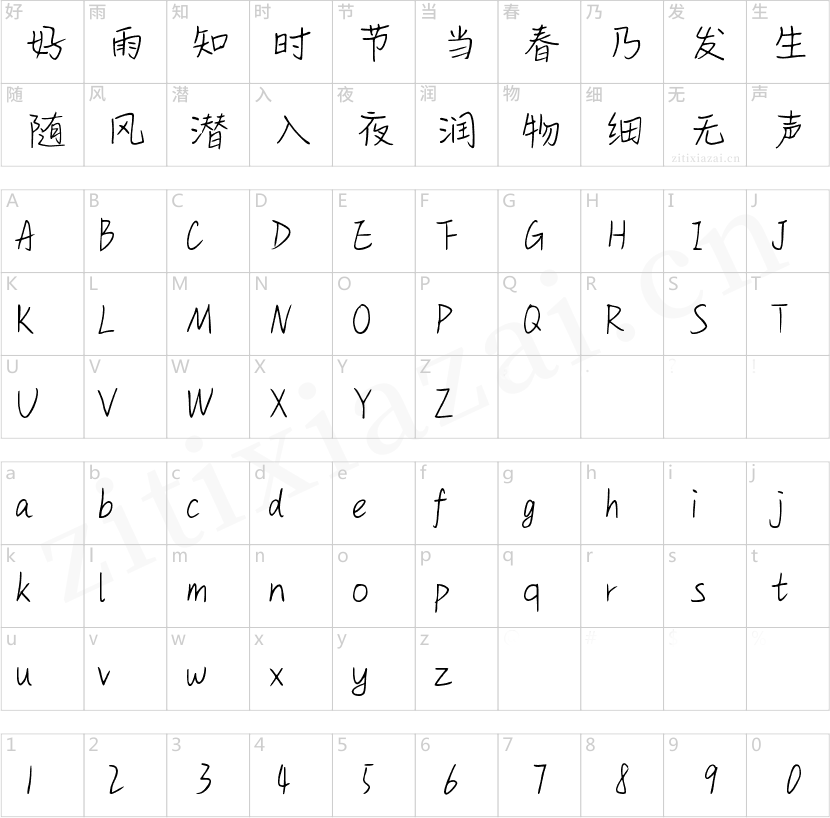
Aa嘟嘴卖萌
Aa嘟嘴卖萌字体
Aa嘟嘴卖萌是一款非常具有艺术性的字体,它的设计灵感来源于对古典艺术的研究,同时又融入了现代字体设计的元素。字形优美,笔画粗细变化自然,给人以大气、典雅的感觉。Aa嘟嘴卖萌是一款既传统又现代的字体,它的设计充满艺术感,美观大方,实用性也非常强。无论是对于设计师还是对于普通读者来说,都是一种非常不错的字体选择。Aa嘟嘴卖萌适合用于具有艺术感的场合,比如海报、宣传单张、书籍封面等。由于其字形流畅且具有动态感,也适合用于大量的文本排版,如报纸、杂志等。